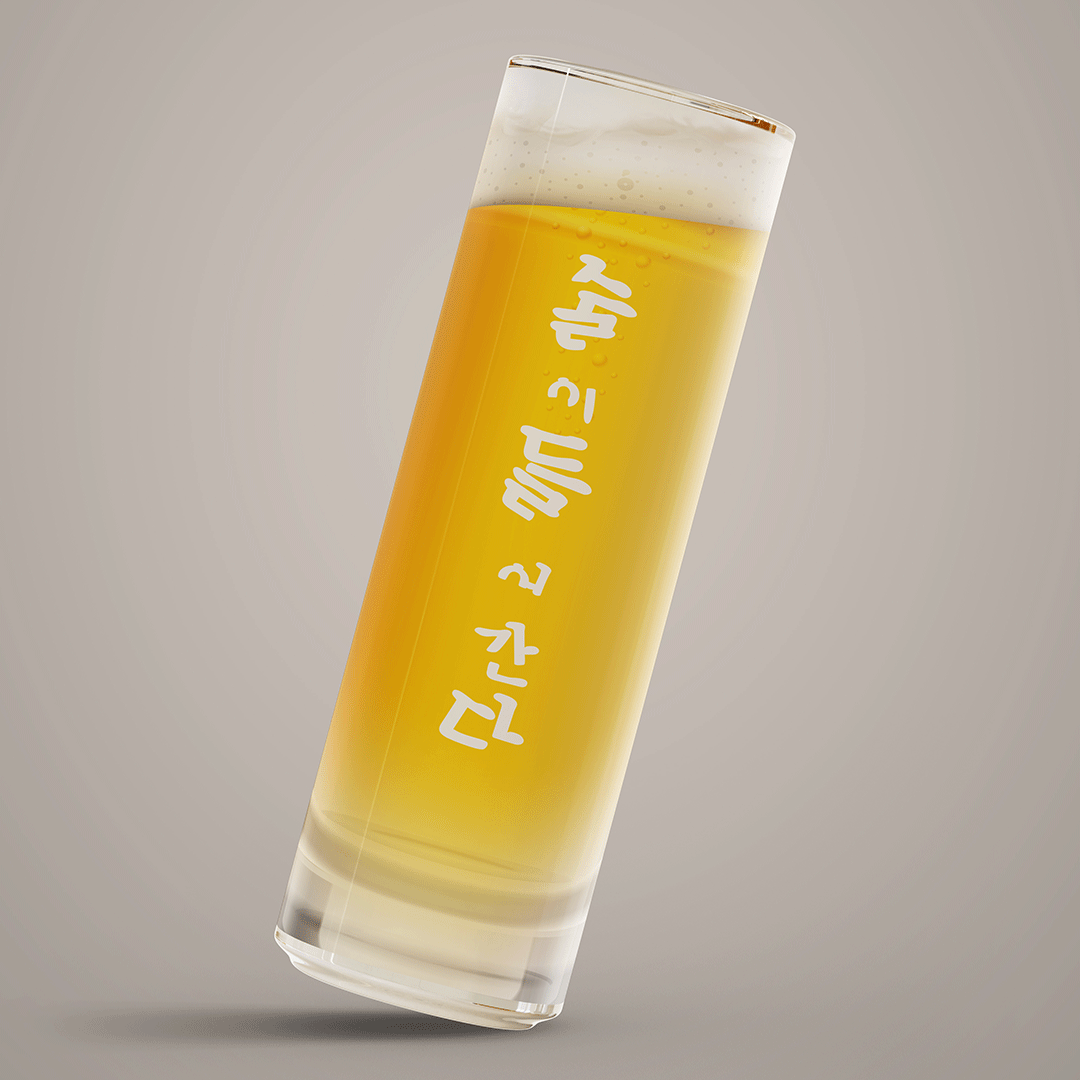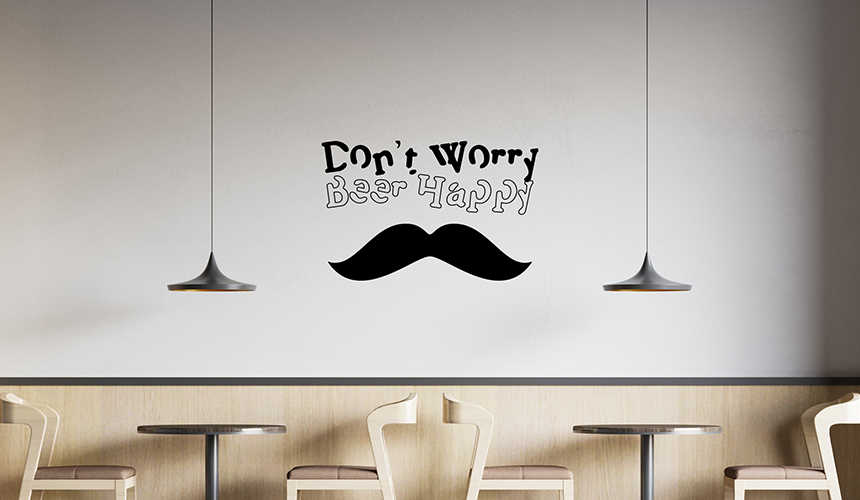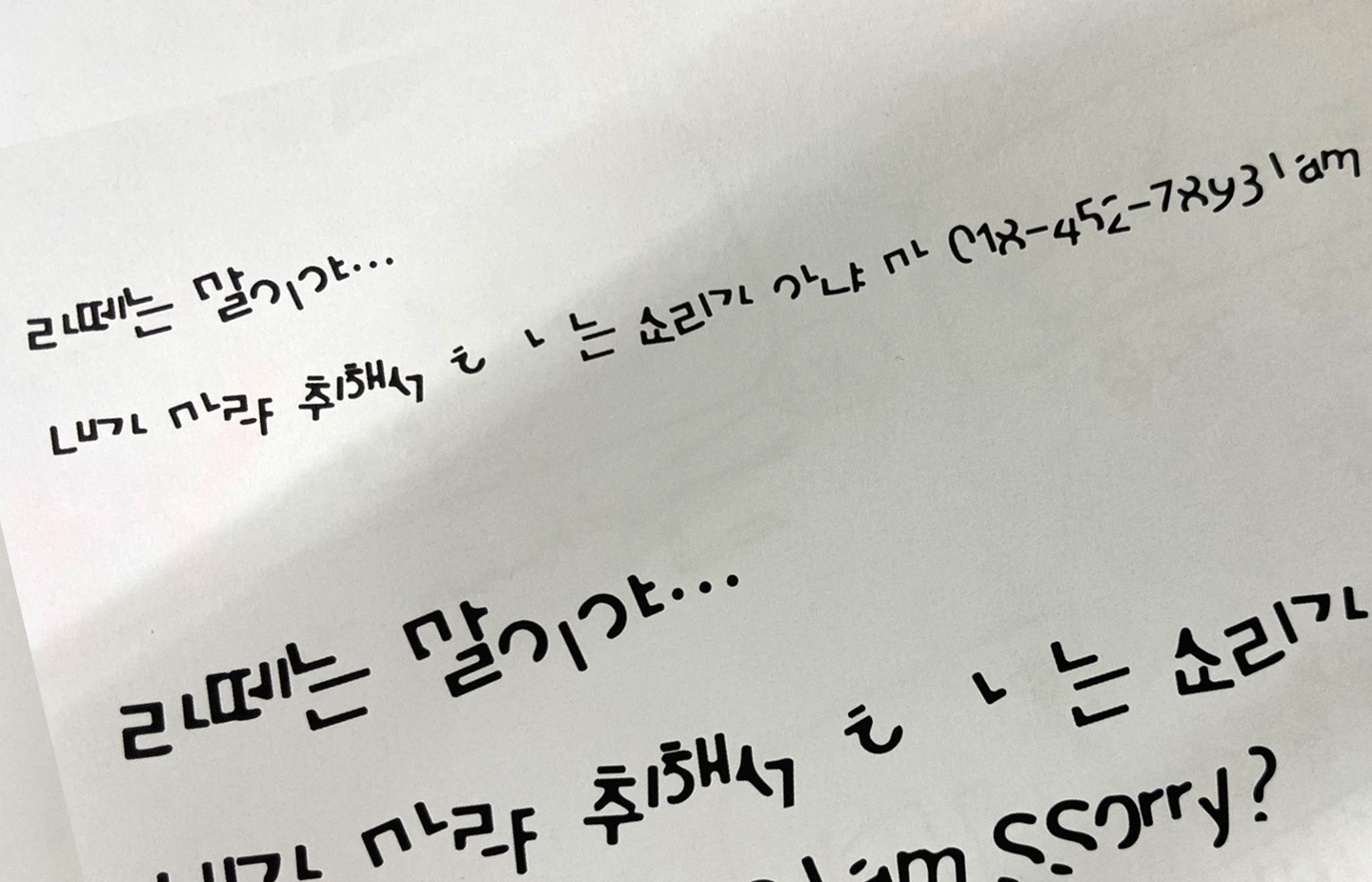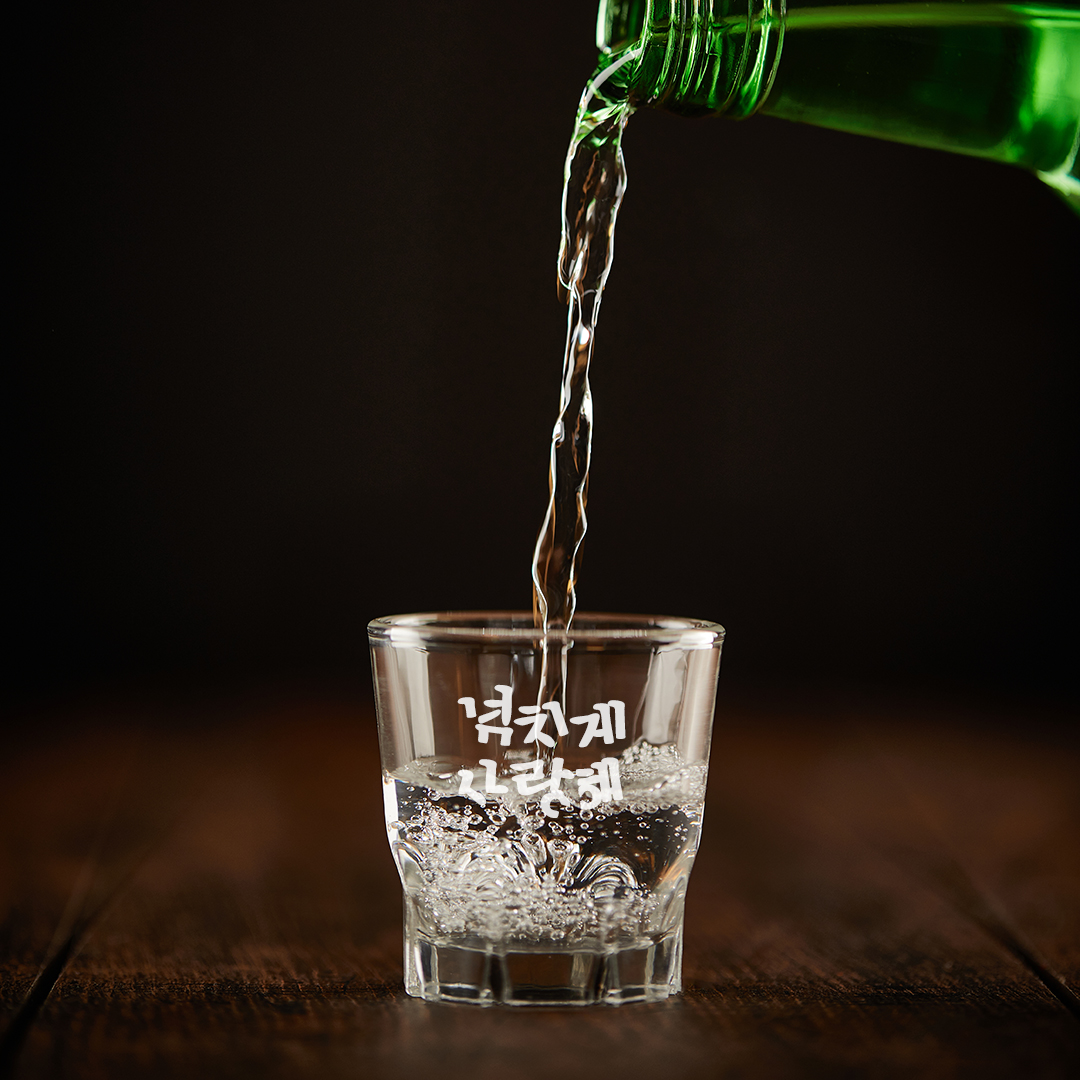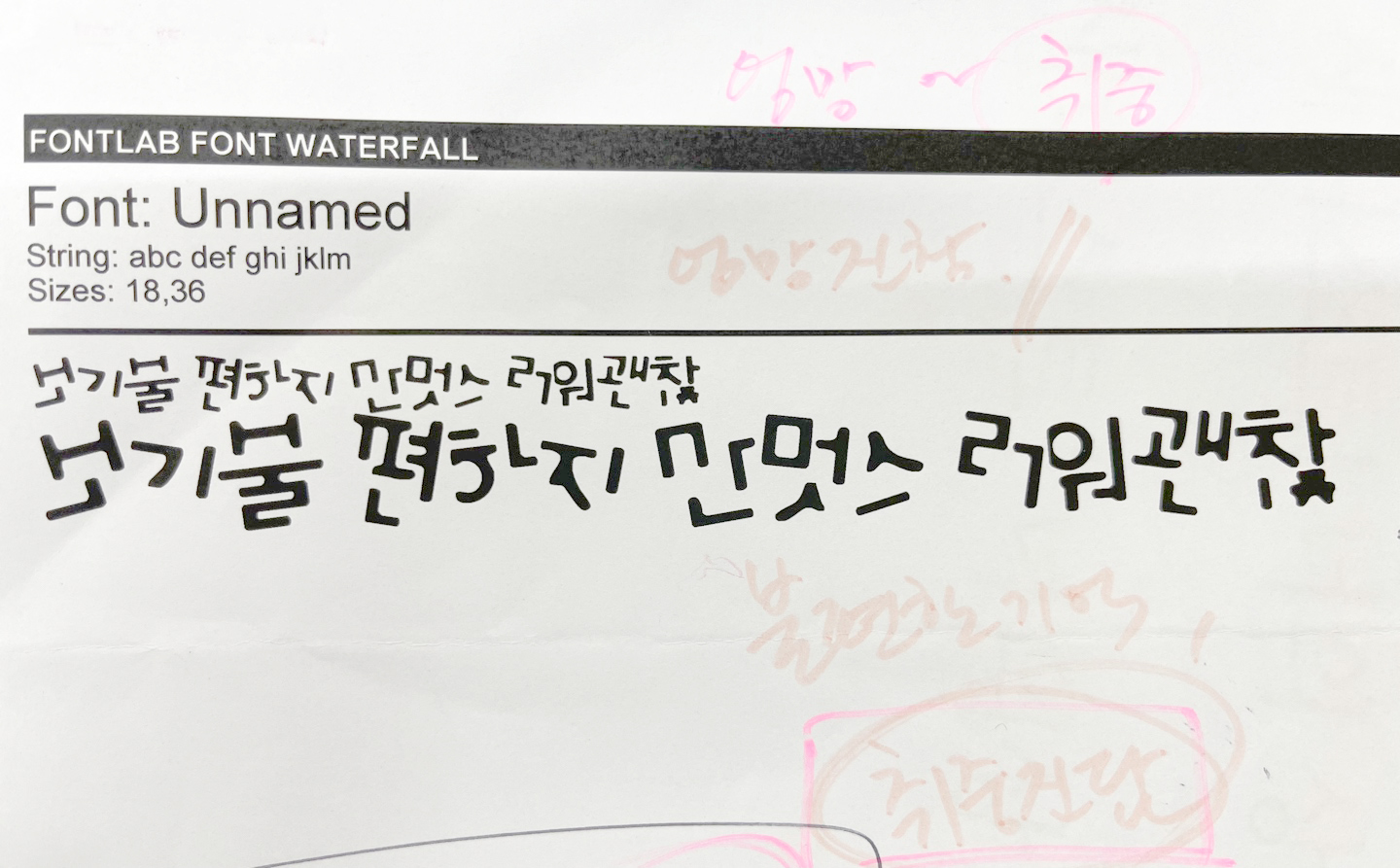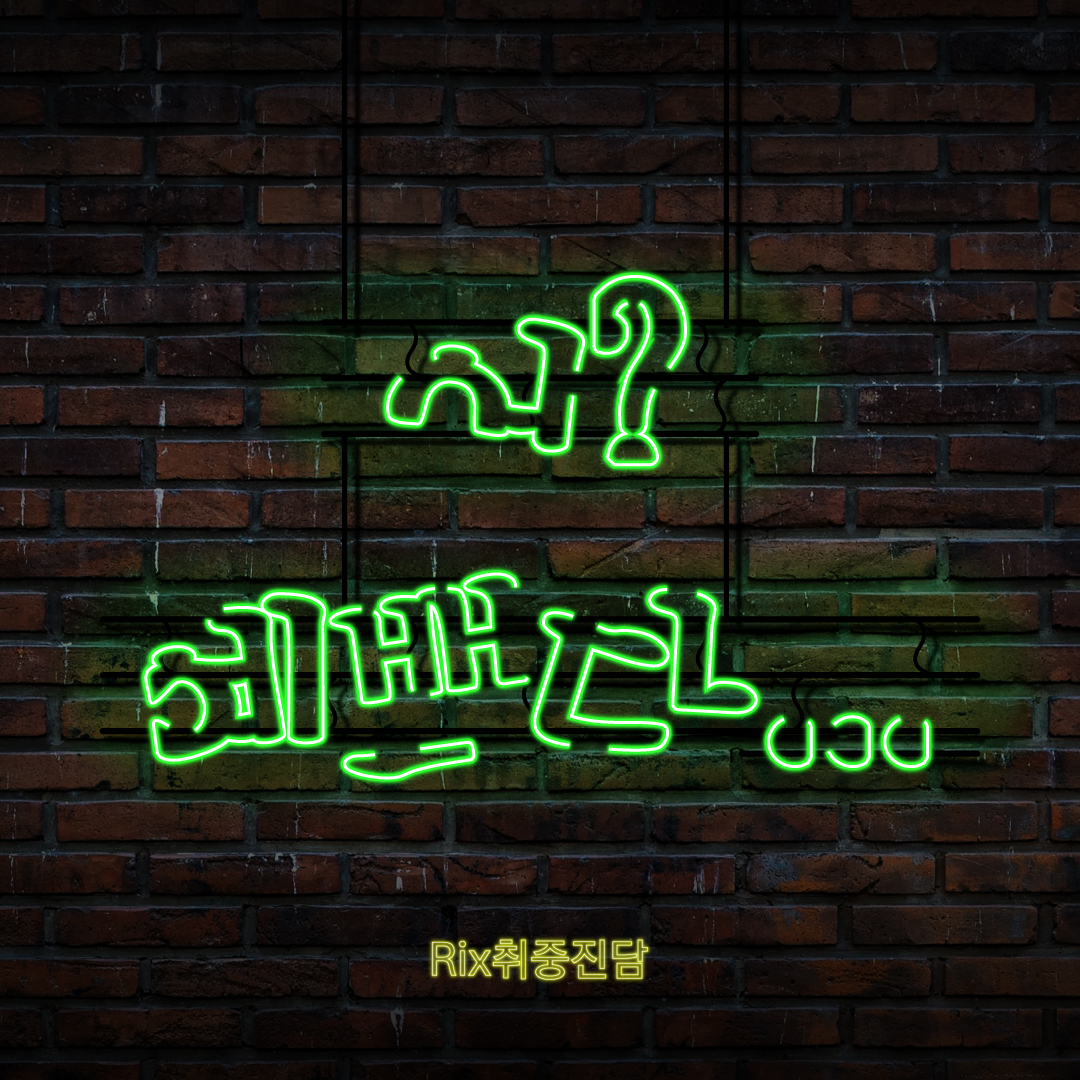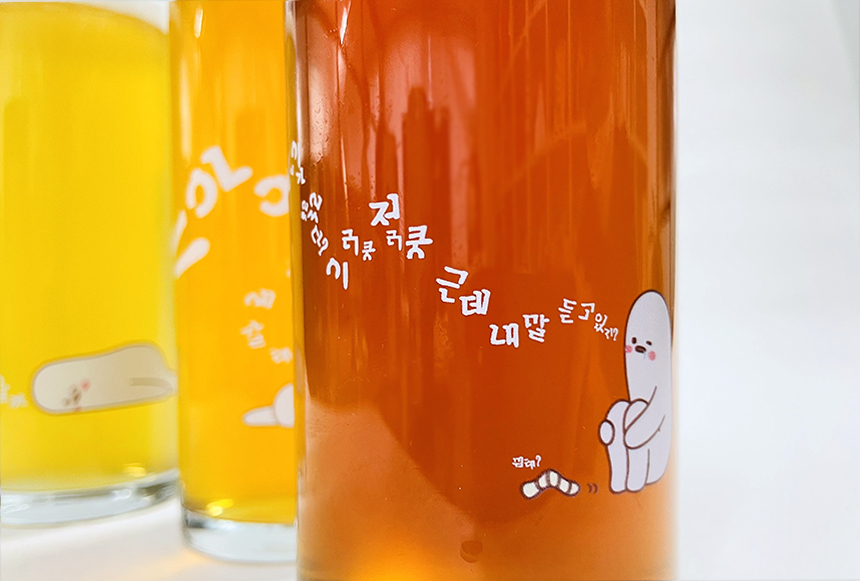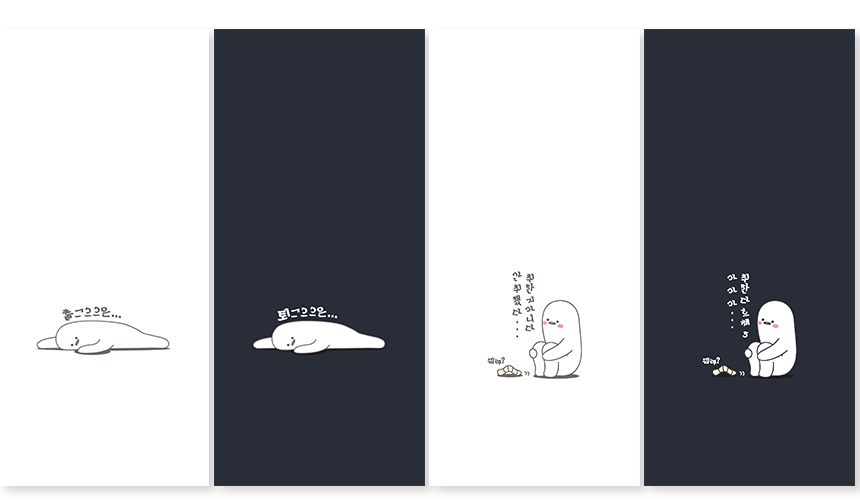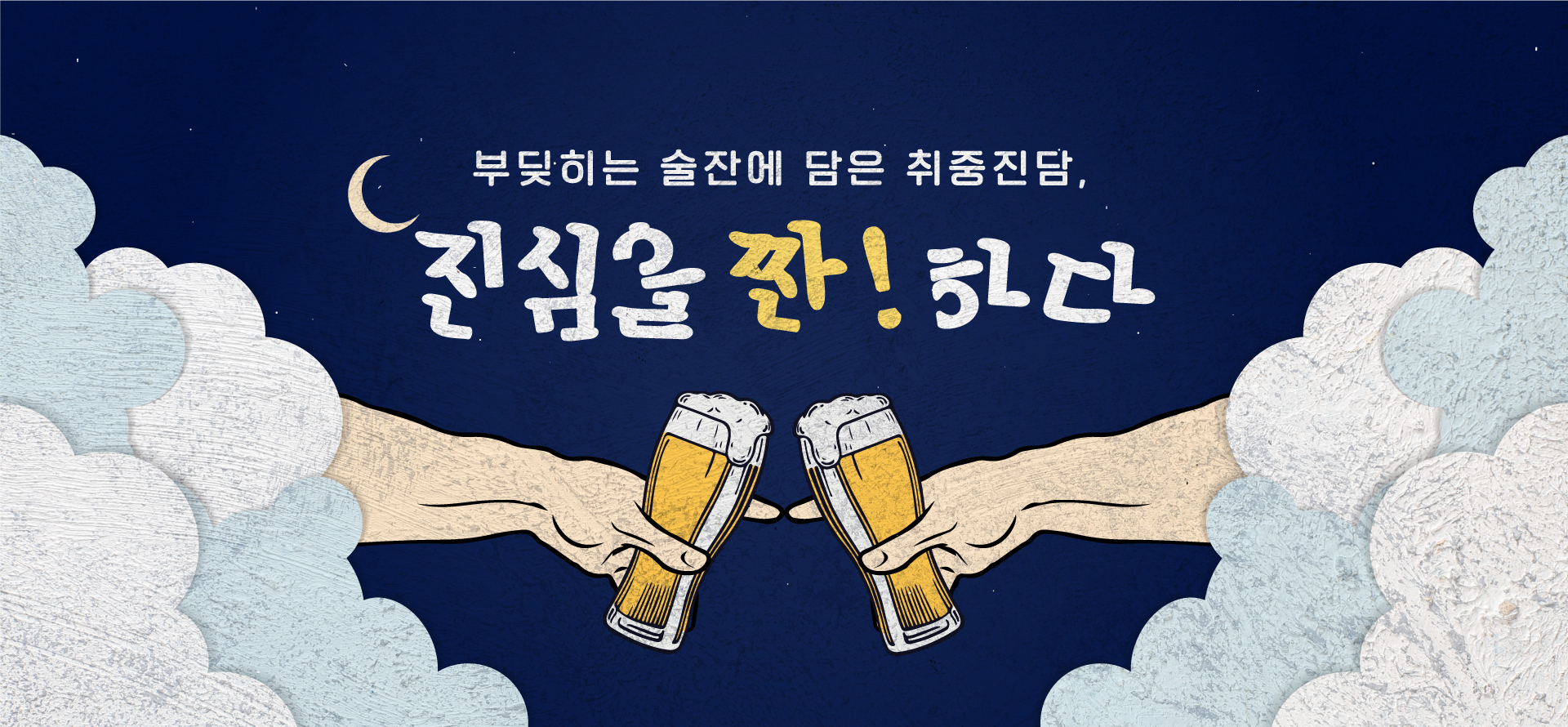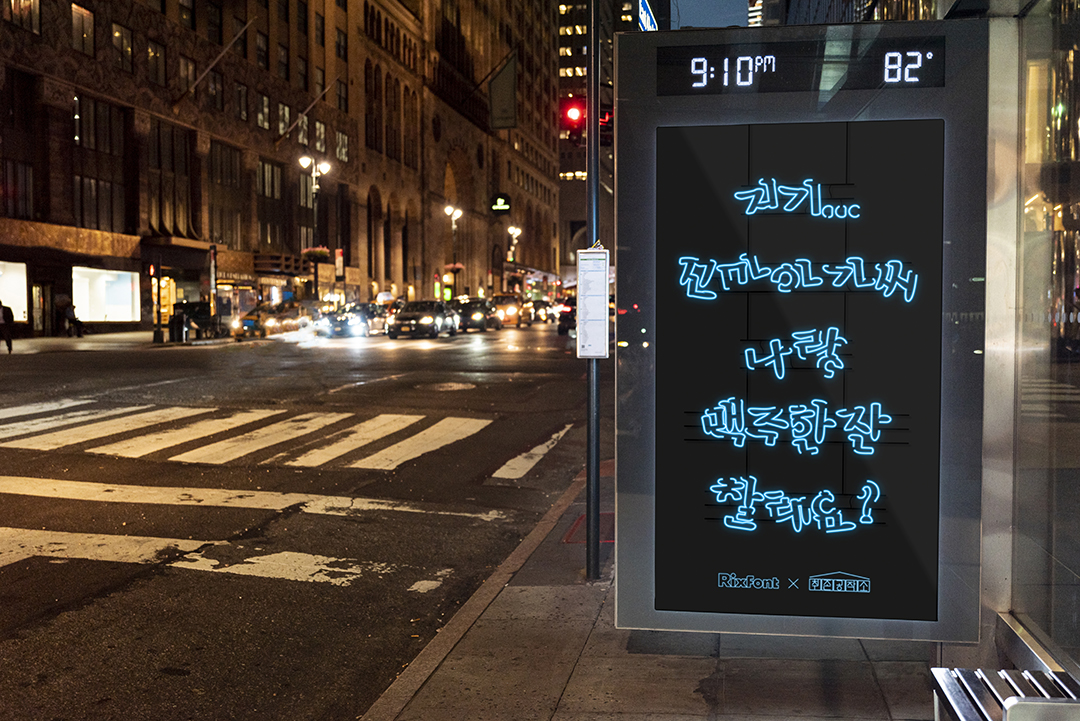
진심을 짠! 하다, Rix취중진담
부딪히는 술잔에 진심을 전하다 -
북적북적 시끄러운 술집에서 친구와 나누던 술 한 잔, 사랑하는 사람들과 함께했던 따뜻한 대화들이 참 그리운 요즘입니다. 술김에 용기 내 했던 말들 속에는 취했지만 취하지 않았던 그때의 추억과 시간이 담겨있습니다. 어쩌면 이불킥을 부르는, 오열각인 진심들을 하나씩 꺼내보게 하는 독특하고 특별한 폰트를 소개합니다. 아 참, 여름맞이 시원한 이벤트도 함께해요!
제작자 인터뷰_취중진담 폰트 제작기
안녕하세요. 먼저 간단하게 소개 부탁드립니다!
폰트릭스 전략기획실 김원준입니다. 전략기획을 주로 하고 있습니다. 오랜만에 폰트 작업을 하게 되었네요.
Rix취중진담체는 폰트명 그대로 취중에 쓴 듯한 글씨 형태가 굉장히 독특한데 어디에서 아이디어를 얻으셨는지 궁금합니다.
지인과 술 한잔 하던 중에 메모를 하게 되었지요. 다음날 보니 삐뚤빼뚤한 것이 누가 봐도 술에 취한 글씨체더군요. 메모를 보면서 폰트로 만들면 어떤 느낌일까 하는 생각에 스케치를 해보았습니다. 나름 재미난 표현이 되어서 작업을 시작하게 되었습니다.
기획 스케치 초안
총 제작 소요시간은 얼마나 걸렸나요? 제작하면서 가장 어려웠던 부분은 무엇이었고 또 어떻게 극복했는지?
글자에서 보이는 취한 느낌의 표현은 자칫 읽기 어려운 상태가 되기도 합니다. 문장에서 보이는 취중의 느낌을 표현하기 위해 꽤 많은 문장 테스트를 했습니다.
글자로서 읽기 힘든 부분을 가려내어 읽을 수 있도록 제작하였는데, 이 두 가지에 꽤 많은 공을 들였습니다. 덕분에 2달여 시간이 소요되었네요.
작업 과정
취존공작소(취향존중 폰트 공작소) 프로젝트의 일환으로 제작된 서체라고 들었는데, 이 폰트는 어떤 부분이 취향 저격이다라고 할 수 있을지?
정갈하고 읽기 편한 폰트는 많습니다. 하지만 가끔 망가진 표현을 위한 폰트는 찾아보기 힘들지 않나요? 타이핑만으로도 취한듯한 표현을 보여준다면 재미있겠죠? 술 한잔 좋아하시는 분들이라면 이해하며 사용하실 것 같고 나름 취향 저격 아닐까요(웃음)
앞으로 또 새로운 폰트 제작 계획이 있나요?
주위의 다양한 상황을 표현한 폰트를 제작해보려고 합니다.
흔들리는 잔들 속에서 네 진심이 느껴진거야🍻
취중진담 서체는 '술 취해 썼던 작은 메모'에서 시작되었어요. '취해서 쓴 폰트는 어떤 모양일까? 이런 글씨도 폰트로 출시할 수 있을까?' 하는 막연한 생각이 기획과 디테일한 작업의 시간을 거쳐 이렇게 폰트로 탄생하게 되었답니다. 이 폰트는 부딪히는 술잔에 취해 흔들흔들 요동치는 내 마음 같을 수도 있고, 보는 사람에 따라 행복했거나 때론 가슴 아팠던 기억이 떠오를 수도 있겠죠. 그럼에도 웃고 넘길 수 있는 즐거운 추억들이 더 많길 바라며!
술은 안 취해, 내가 취해
Rix취중진담 폰트는 취한 듯 비틀거리는 글줄과 중간중간 끊긴 글씨로 위트가 느껴지는 형태, '나 지금 진지해' 궁서체를 닮은 굵은 명조 스타일로 제작된 서체입니다. 술에 취하면 글자가 잘 읽히지 않죠? 기존 폰트들과 다르게 가독성이 떨어지는 것이 이 폰트의 매력(?)입니다. 그동안 무료로 배포되었던 RixFont의 열정도체, 할매의꽃담요체와 같이 누구나 '무료'로 사용할 수 있는 서체로 위에서 잠깐 언급했던 취존공작소의 세 번째 프로젝트 폰트입니다.
취존공작소🤡
한 명의 취향도 존중하는 폰트를 만드는 폰트 취향 존중 프로젝트로, "저는 이런 폰트가 좋아요!"하고 자유롭게 외칠 수 있는 공간입니다. 가독성보다 독특함을, 완성도보다 신선함을 주는 재밌는 폰트를 만들고 함께 공유하고자 기획한 폰트 플랫폼입니다.
그런데 이 폰트, 어디에 써?
폰트가 특이해서 이걸 어디에 써야 하나.. 고민되시나요? 생각보다 다양한 활용이 가능하다는 점. 놀라지 마세요🙃
일단 명조체의 기본 형태를 갖고 있으면서 굵은 제목용 서체이기 때문에 타이틀로 사용하기에 좋습니다. 글씨체와 어울리는 문구나 타이틀로 포스터나 배너, 네온사인 등 디자인에 활용해 보세요.
짧은 문구를 사용해 굿즈나 제품 디자인에도 활용 가능합니다. 레터링 스티커, 잔이나 컵, 패키지 등 다양한 디자인에 접목하여 유니크하게 활용할 수 있어요.
자체제작 맥주잔
칼퇴 기원 배경화면
출퇴그으은 시리즈 / 안취했다 시리즈